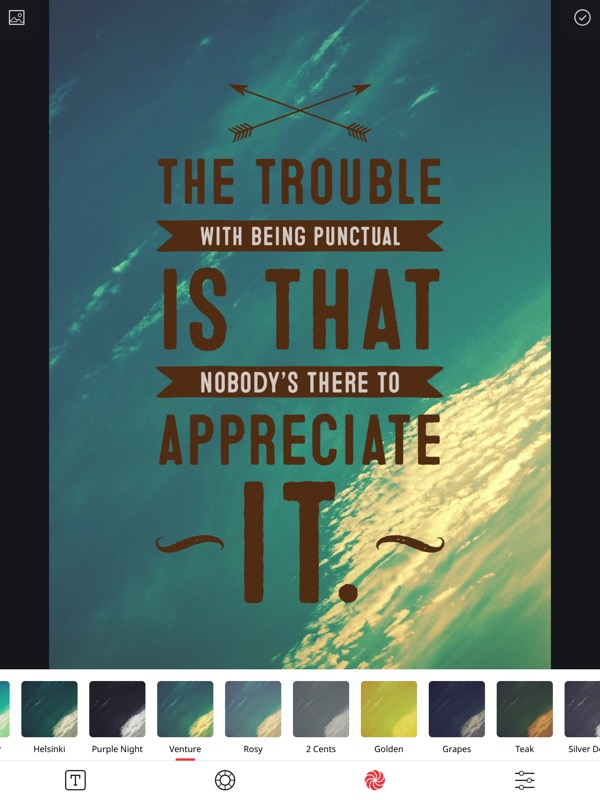
Sinnsprüche, Zitate und andere Texte sehen dank Apps wie Retype auf Fotos besonders gut aus.
Nach meinen ersten Versuchen mit Retype fällt vor allem eines auf: Die direkte Nähe zur Konkurrenz-App Typorama (App Store-Link), die bei mir schon seit einiger Zeit zufriedenstellend zur Anwendung kommt. Auch Retype erlaubt es dem Nutzer, entweder aus einem Archiv oder aus der Camera Roll importierte Bilder mit verschiedenen Schriftstilen zu versetzen, Filtereffekte und Unschärfe auf das Hintergrundbild anzuwenden sowie die Textfarbe zu ändern.
Besonders praktisch: Wer nicht gleich über einen eigenen Text verfügt, kann sich in Retype durch verschiedene englischsprachige Sprüche inspirieren lassen. Insgesamt stehen in der Anwendung 15 unterschiedliche Schriftstile zur Verfügung, die über Antippen des entsprechenden Buttons außerdem nahezu unendliche Varianten des gewählten Designs anbieten. Die so erstellten Layouts lassen sich über einfache Ziehgesten auf dem Bildschirm beliebig in ihrer Größe anpassen und verschieben.
Vor- und Nachteile von Retype
Im direkten Vergleich zu meiner bisher favorisierten App Typorama bietet Retype vor allem im Bereich der Schriftarten einige ansehnliche Vorteile durch hochwertiger wirkende Designs. Dafür muss man mit einigen Einschränkungen hinsichtlich der Bearbeitungsmöglichkeiten Vorlieb nehmen: So kann unter anderem der Schattenwurf der Schriften nicht verändert werden, ebenso ist kein Zuschnitt des Bildes auf das beliebte 1:1-Format möglich. Retype hingegen offeriert eine Option zum Umkehren des Layouts, die insbesondere bei hektisch wirkenden Hintergründen praktisch ist.